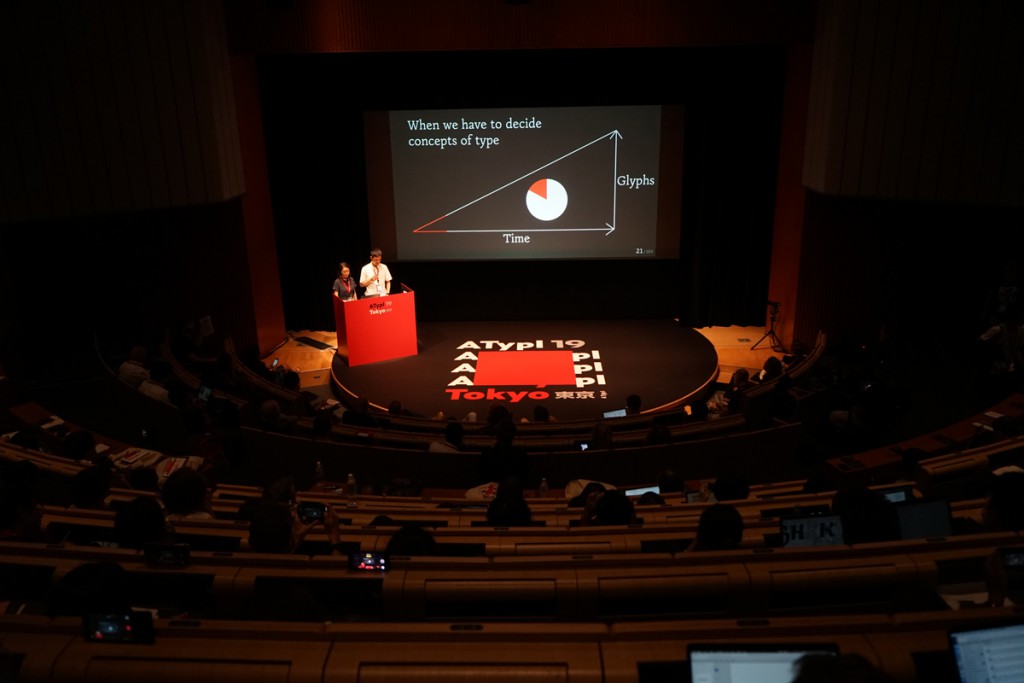
산돌, ATypI에서 CJK 제작 노하우 공개
산돌이 지난 4일부터 7일까지 나흘간 일본에서 열린 ATypI 컨퍼런스에서 CJK(한글, 한자, 가나자) 폰트를 제작하는 제작 과정과 노하우를 공개했다. ATypI 컨퍼런스는 1957년 스위스에서 시작해 올해로 63회째를 맞이한 세계 최고 권위의 타이포그래피 컨퍼런스다. 매년 각기 다른 도시에서 전세계의 폰트 디자이너와 폰트 회사, 그래픽 디자이너 등이 모여 폰트와 타이포그래피, 언어 등에 대해 논의하고 공유한다.
산돌은 이번 컨퍼런스에서 ‘수정이 즐거운 디자인’과 ‘건축가처럼 한글 짓기’라는 발표를 통해 획이 많고 복잡한 한글, 한자, 가나자를 디자인 하는 산돌만의 개발 체계와 디자인 방법론을 제시했다. 또한 앞으로 변화될 CJK 폰트 디자인 환경을 전망하며 산돌이 연구하고 있는 AI(인공지능)과 딥러닝 기술에 대해서도 소개했다. 이번 발표를 통해 산돌은 점차 발전하고 있는 디자인 프로세스와 기술이 CJK 폰트의 생산 시간을 단축하고, 개발 부담을 줄여 양질의 폰트를 생산할 수 있는 주요한 동력이 될 것이라는 기대를 드러냈다.
발표는 심우진 산돌 한글디자인연구소장과 김초롱 폰트디자인팀장, 이도희 폰트디자이너가 각각 맡았다. 심우진 소장은 책과 활자의 디자인 방법론을 중심으로 교육, 출판, 실무에서 활동 중이며 저서로는 『본문 조판 참고서』(2015), 『타이포그래피 사전』(공저, 2015) 등이 있다. 김초롱 팀장은 프랑스 브장송 보자르(ISBA Besancon)와 아미앙(ESAD Amiens)에서 서체 디자인을 공부하고 산돌에서 한글 및 라틴 문자 서체를 디자인했다. 이도희 디자이너는 서울대학교에서 시각디자인을 전공하고 산돌에서 다양한 글로벌 브랜드의 폰트를 디자인했다.
심우진 소장은 “이번 ATypI 컨퍼런스에서의 발표는 산돌과 산돌의 디자이너들의 보유한 기술과 노하우가 세계 최고 수준임을 다시 알릴 수 있는 좋은 기회였다”며 “산돌의 디자인 철학인 ‘행복한 디자인’을 위해 보다 효율적이고 생산적인 프로세스와 방법론을 계속해서 연구해 나갈 예정”이라고 말했다.
김초롱 팀장은 “작년에 이어 올해도 ATypI 컨퍼런스에서 발표를 하게 되어 개인적으로 영광”이라며 “작년이 산돌의 새로운 한글 폰트를 전세계에 알리는 자리였다면 올해에는 많은 글로벌 프로젝트들을 통해 축적된 산돌의 노하우를 세계 각국의 폰트 회사, 폰트 디자이너들에게 알릴 수 있는 기회가 된 것 같다”고 소감을 밝혔다.
이밖에도 산돌은 해외 폰트 디자이너를 대상으로 한글 디자인 워크샵도 진행했다. 워크샵에 참여한 각국 디자이너들은 산돌이 실제 진행한 글로벌 프로젝트를 바탕으로 기존 라틴 폰트에 한글 폰트를 매칭하여 디자인하거나 UI・UX에 어울리는 한글 디자인을 직접 체험해보는 시간을 가졌다. 진행은 산돌 김초롱 팀장과 미국에서 활동하고 있는 폰트 디자이너 아론 벨(Aaron bell, Sajatypworks)이 맡았다.